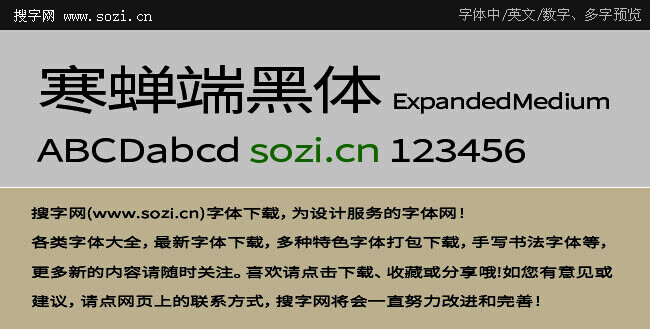
寒蟬端黑體ExpandedMedium
搜字網(wǎng)給大家提供一款寒蟬端黑體ExpandedMedium中文字體下載,寒蟬端黑體是基于思源黑體進行調(diào)整的黑體字體,在原字體風格上重新插值生成,Expanded系列的寒蟬端黑體是思源黑體的寬體版本。適用于標題設(shè)計、海報設(shè)計、書籍排版以及網(wǎng)頁設(shè)計等應(yīng)用。